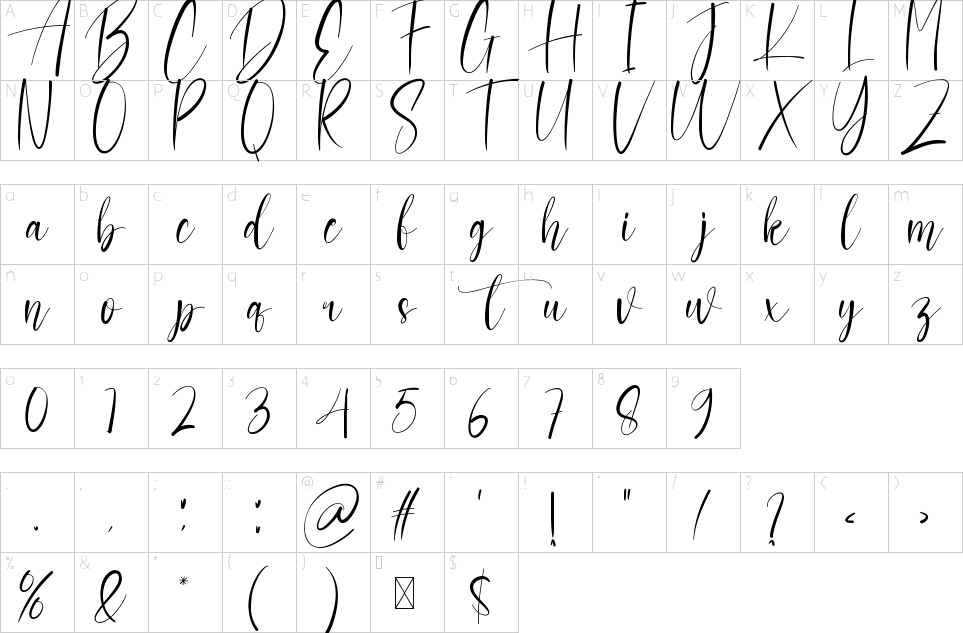
Amsterlove Font – Download Grátis
A fonte gratuita Amsterlove é uma escolha suave e elegante, perfeita para projetos digitais de todos os tipos, da web aos relatórios de apresentações em PowerPoint. Ela foi criada por scratchones e já foi baixada mais de 2,171 vezes. Com sua tipografia fluida e levemente românica, a Amsterlove pode transformar o modo como você exibe texto, tornando o seu design mais atraente. A versão disponível é compatível com sistemas operacionais Windows e Mac, tornando-a uma opção versátil para designers que desejam incorporar essa fonte em seus projetos. Se você está procurando por uma fonte agradável que vai além do básico, a Amsterlove é uma excelente opção para sua próxima criação digital.